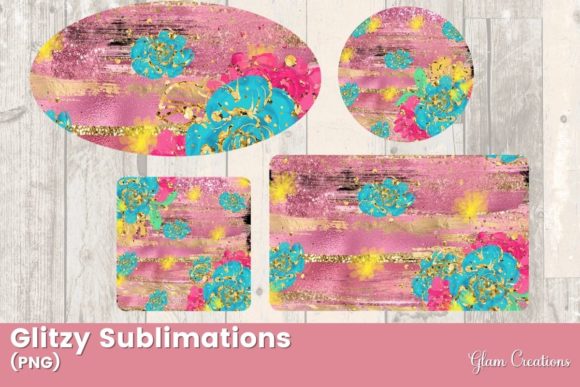
Glitzy Sublimations
適切なデザイン要素を見つけるのは難しい場合がありますが、Glitzy Sublimationsは作品を即座に引き立てる優れたコレクションを提供します。
POD(オンデマンド印刷)製品、結婚式の招待状、またはソーシャルメディアのグラフィックを作成している場合でも、Glitzy Sublimationsは理想的です。